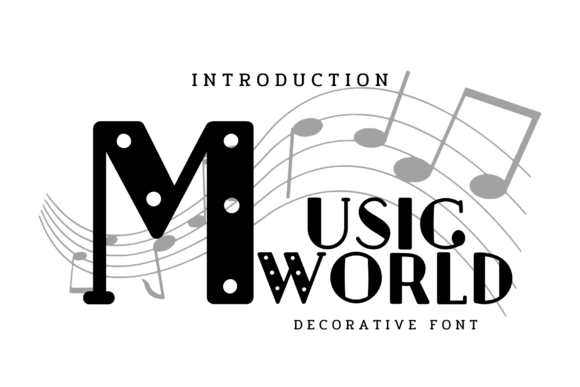
Music World
適切なデザイン要素を見つけるのは難しい場合がありますが、Music Worldは作品を即座に引き立てる優れたコレクションを提供します。
POD(オンデマンド印刷)製品、結婚式の招待状、またはソーシャルメディアのグラフィックを作成している場合でも、Music Worldは理想的です。